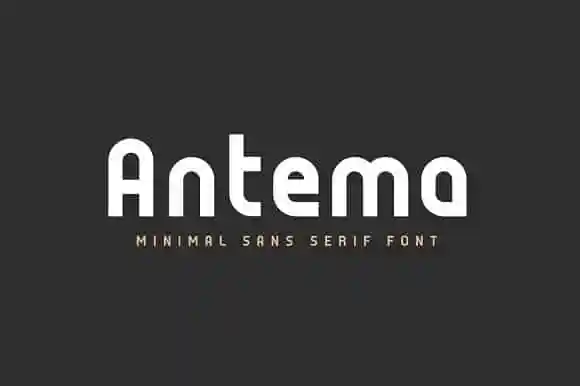
Introduzimos Antema Minimal Font! Esta é uma fonte premium criada pelo designer Seceme Shop, agora disponível gratuitamente para download em seu site oficial, 178-MC. Desenvolvida com um enfoque puramente moderno e geométrico, a Antema é uma fonte sans-serif que se destaca pela sua design claramente geometrico e minimalista. Suas linhas simples e leves tornam-na perfeita para uso em diversas aplicações digitais. Seja para criar materiais de marketing ou desenvolver seu próprio projeto gráfico, Antema traz um equilíbrio elegante entre simplicidade e força visual. Com uma gama de pesos disponíveis, é uma opção versátil que certamente enriquecerá suas criações digitais. Não perca esta oportunidade única para adquirir essa fonte premium em sua forma gratuita hoje!